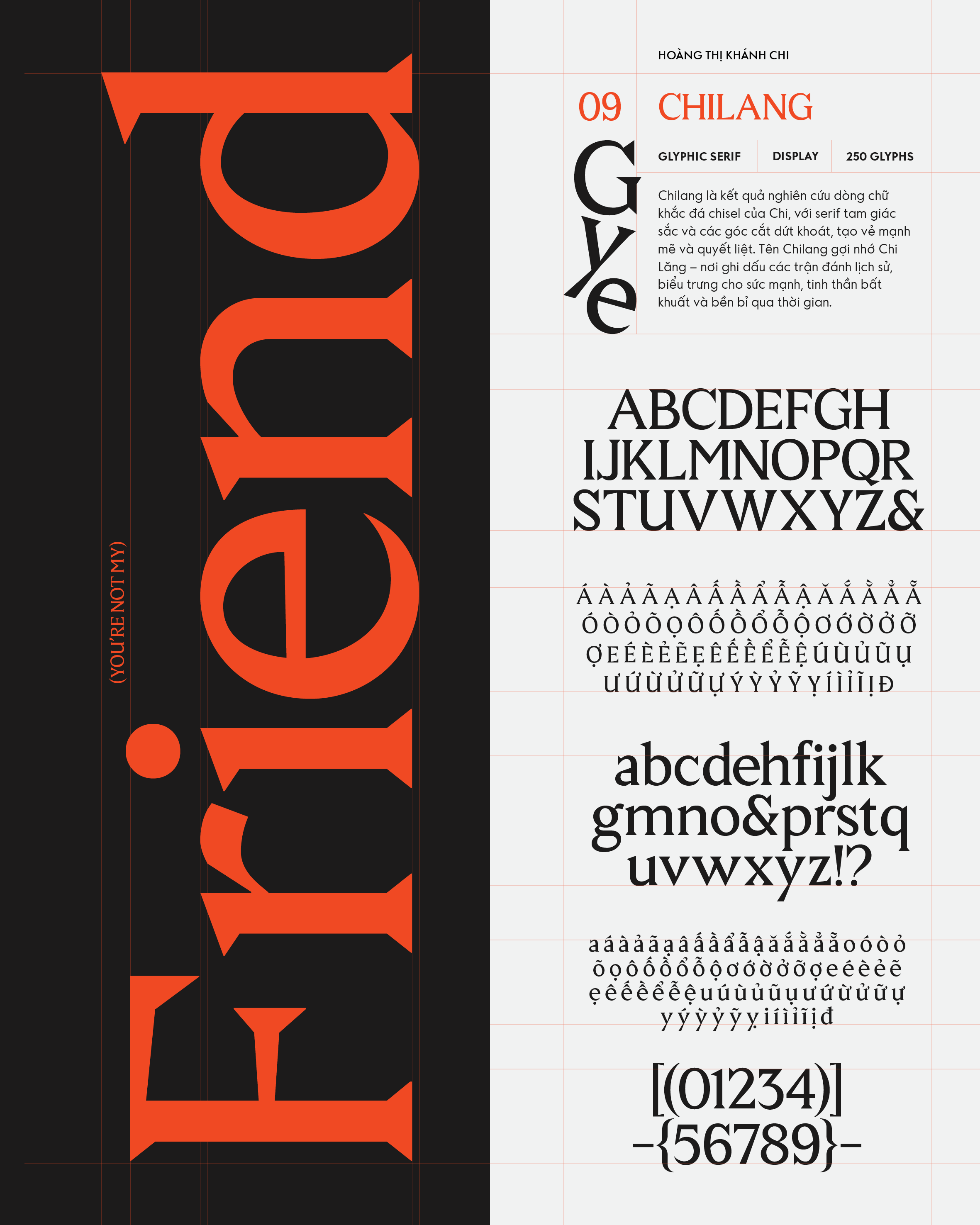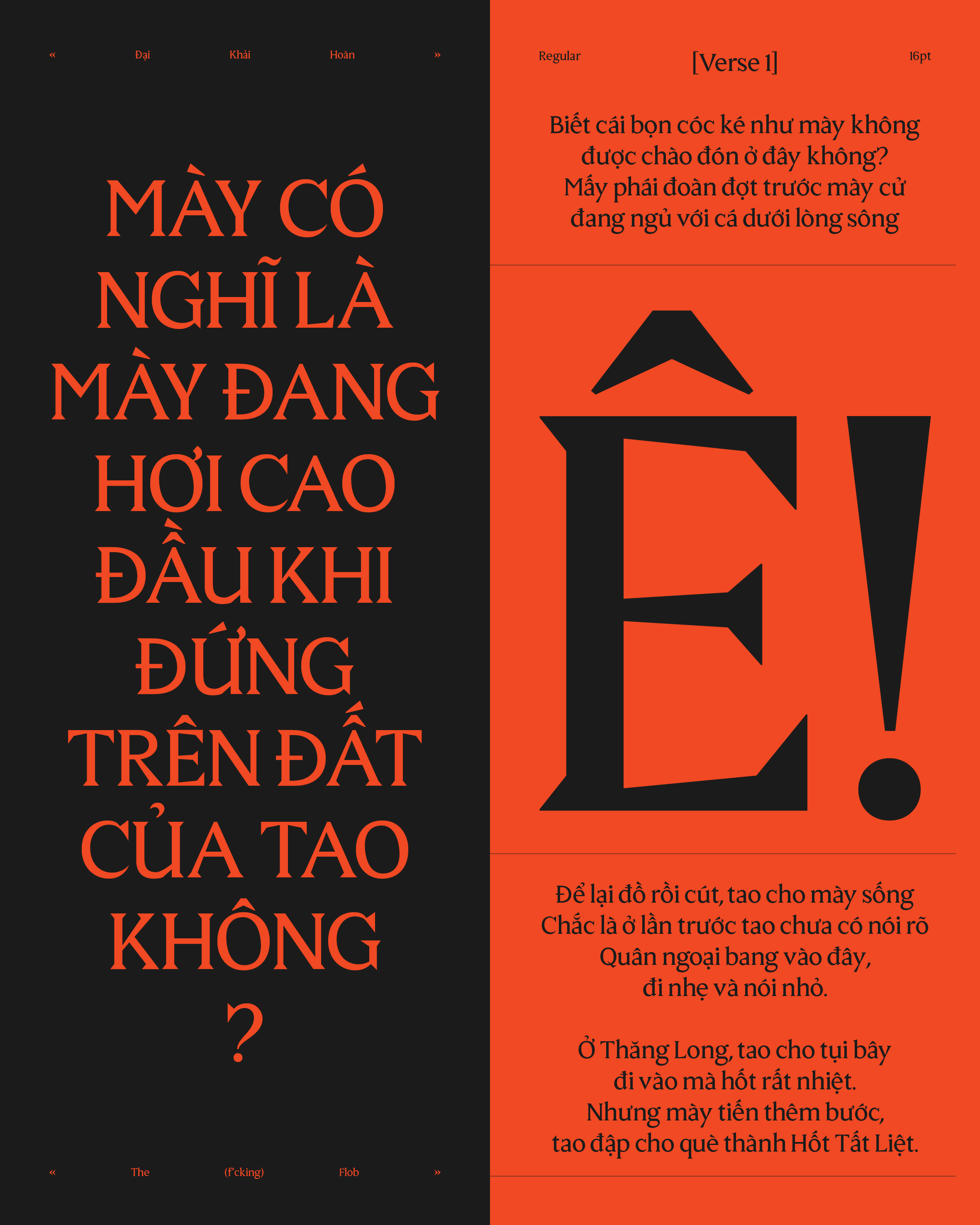
Chilang
Về Chilang: Chilang là kết quả nghiên cứu dòng chữ khắc đá chisel của Chi, với serif tam giác sắc và các góc cắt dứt khoát, tạo vẻ mạnh mẽ và quyết liệt. Tên Chilang gợi nhớ Chi Lăng – nơi ghi dấu các trận đánh lịch sử, biểu trưng cho sức mạnh, tinh thần bất khuất và bền bỉ qua thời gian.
Glyphic Serif
Display
Hoàng Thị Khánh Chi